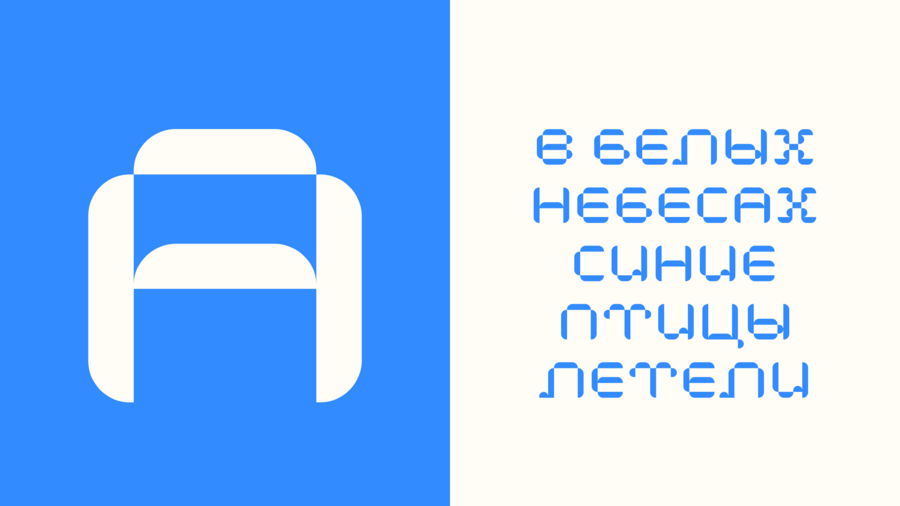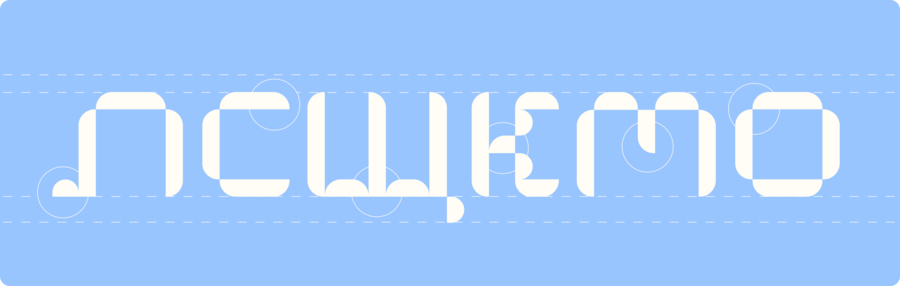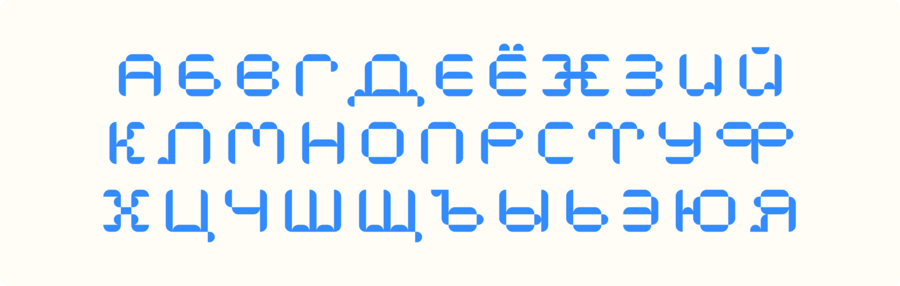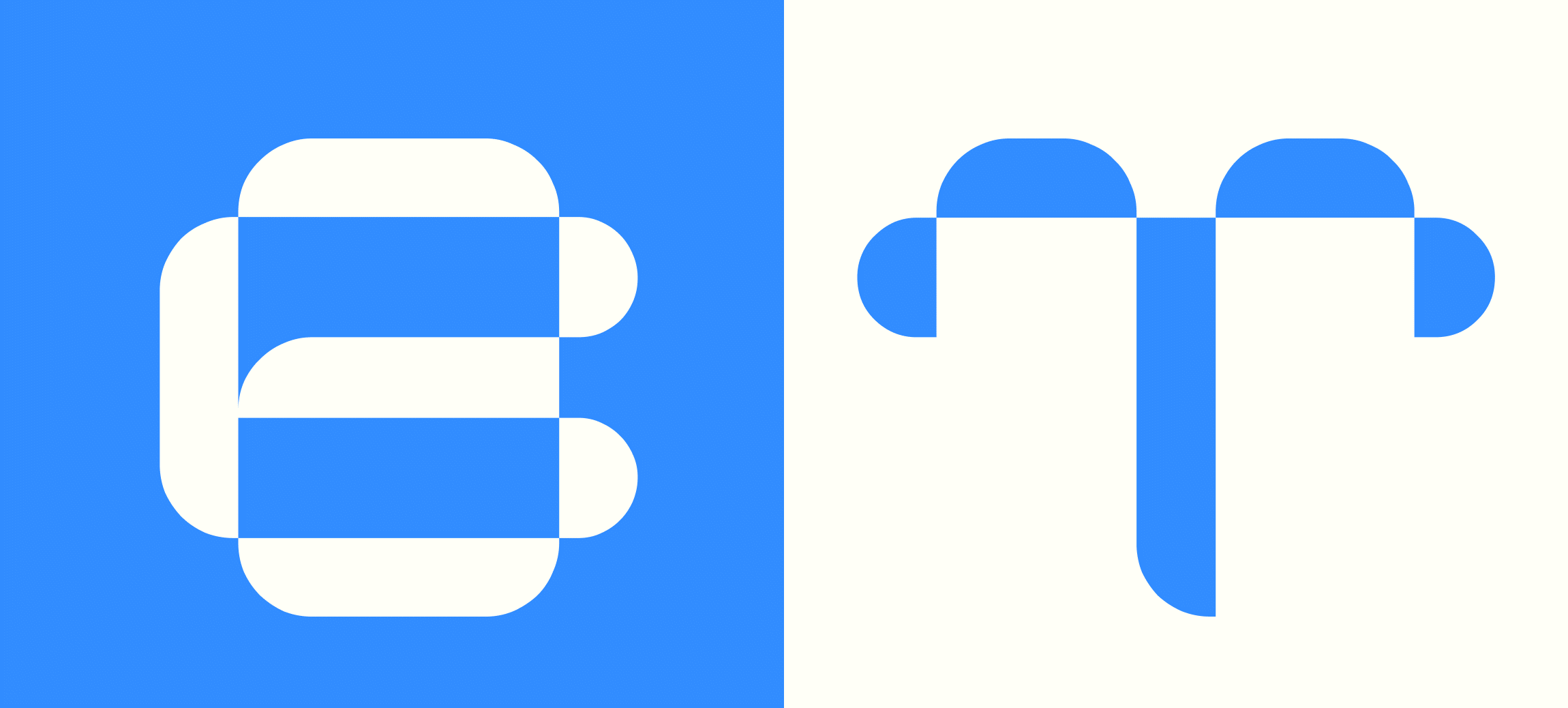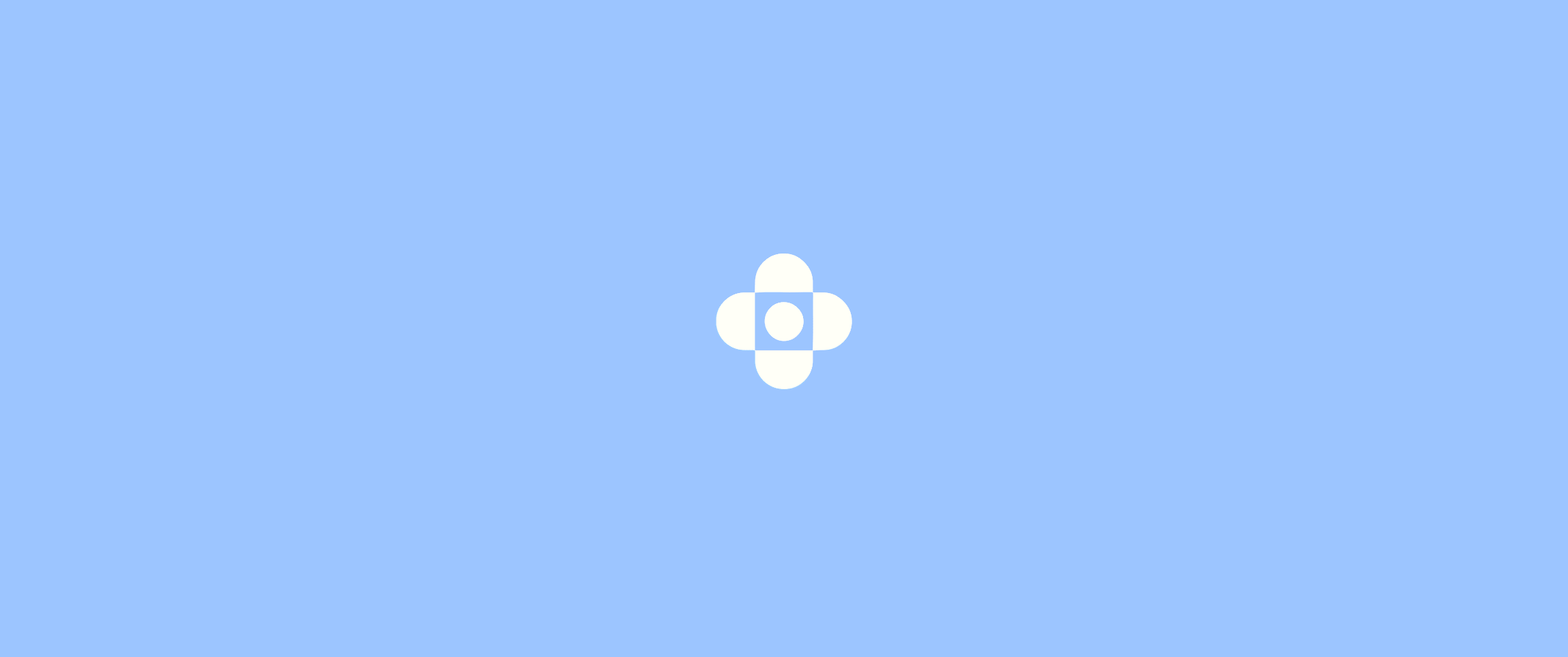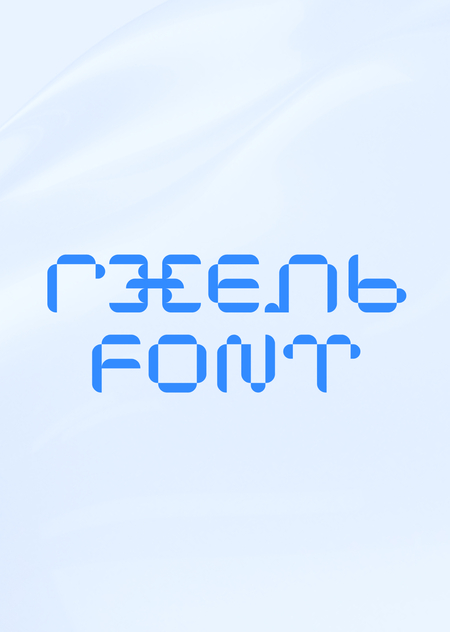
ГЖЕЛЬ typeface — акцидентный шрифт, вдохновленный мягкой пластикой гжельской росписи, которая приобретает новые лаконичные формы в современном переосмыслении